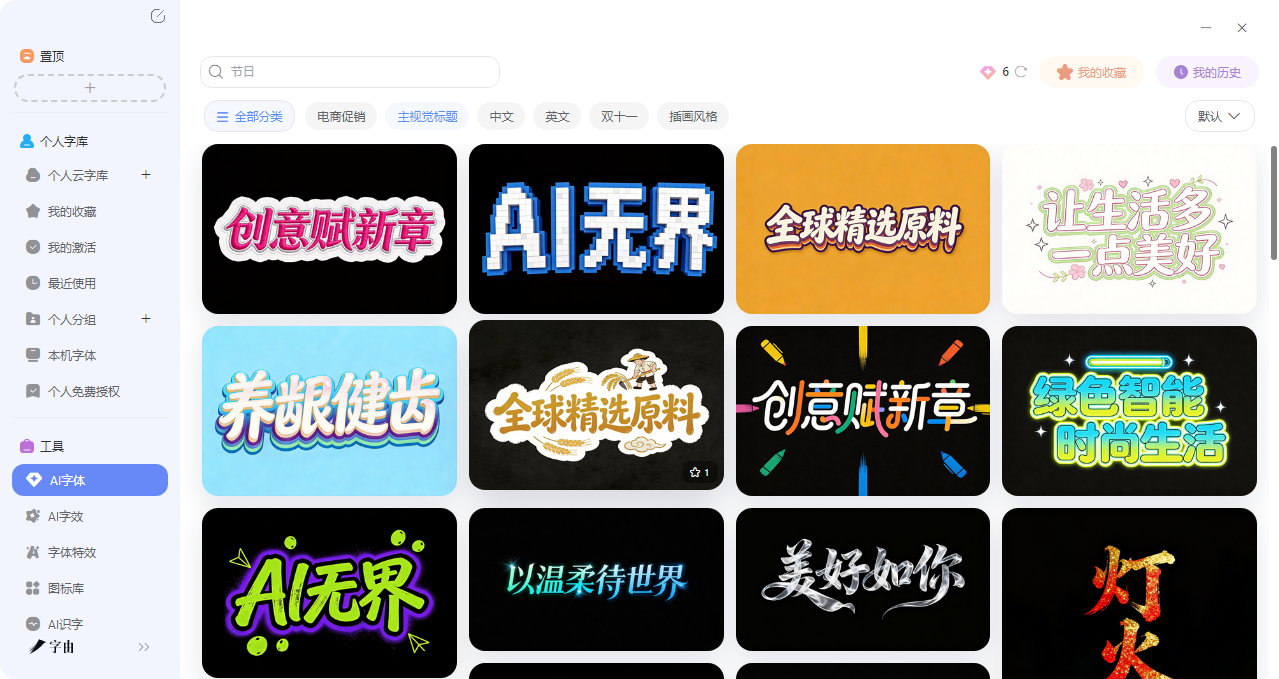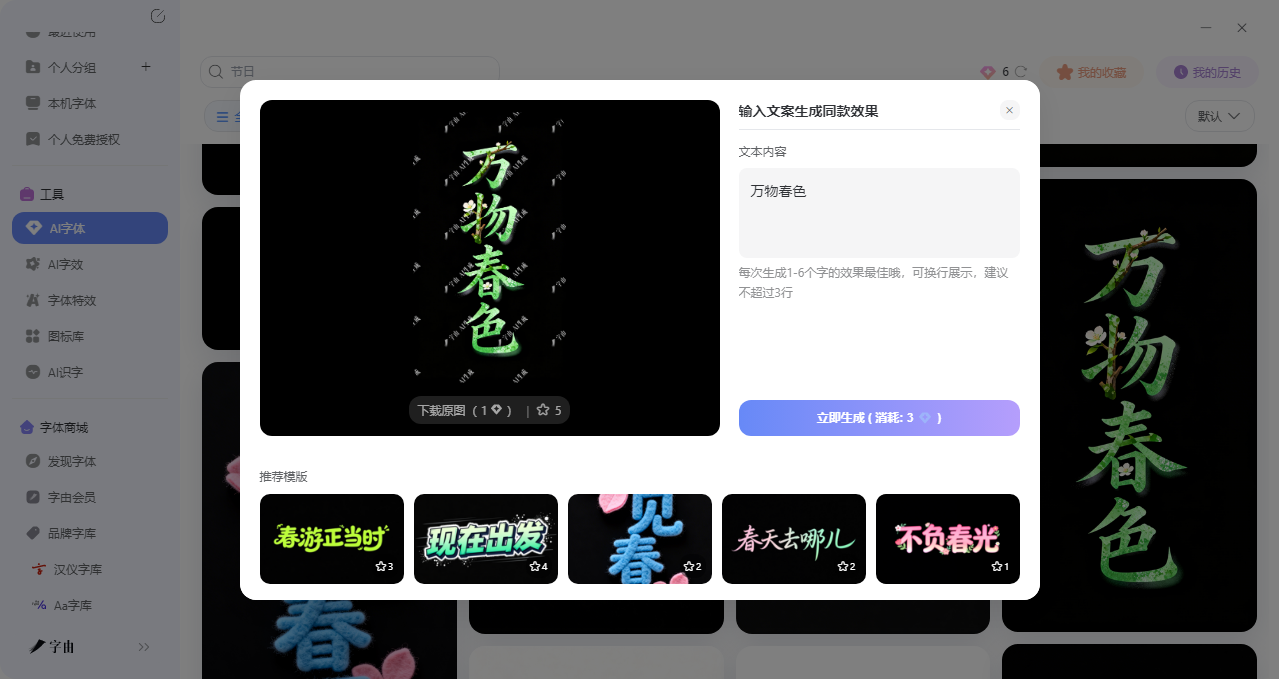
从标题到字幕,视频封面字体用对这个工具就够了
如果你是专门做视频剪辑的肯定都有过这种经历:花了好几天剪辑和拍摄素材,结果上传到视频平台以后播放量却很一般,这样辛苦的付出和平平无奇的收获难免会给自己打击,但是你有没有想过不是你的问题,而是你的封面出了问题?因为封面没有抓住人,观众很难点进来一探究竟。毕竟视频封面就像菜肴的卖相,最起码想让人看了有食欲才能动筷子,字体的选择直接决定了观众愿不愿意点进来。标题要大要醒目,字幕要清晰易读,标签要有风格——同一个封面里,不同位置的文字其实需要不同的字体。有没有一个工具能把这些需求都搞定?字由可以。那么今天这篇就专门讲讲怎么用字由来搞定视频封面字体的所有需求!
1、视频封面用特效AI 字体或更吸引人
视频封面字体的主标题字体是整个封面的视觉中心,这一个一定要足够吸引人、足够抓人眼球。那么字由的AI 字体功能就能够帮你解决如何生成AI 艺术字这个问题。
接下来我将详细介绍怎么用AI 字体做主标题:
第一步:打开AI 字体界面。打开字由客户端,左侧导航栏找到【工具】→【AI字体】,或者从首页【字体工具】→【AI工具】进去。
第二步:选一个适合的视频封面字体。AI字体模板按场景分好了类:电商促销、Banner设计、视频封面、国潮风、科技感等。想做主标题,可以直接点“视频封面”分类,或者按视频类型搜关键词,比如:
- 美食类:搜“诱人”“食欲”“温暖”
- 美妆类:搜“精致”“高级”“优雅”
- 科技类:搜“未来感”“硬核”“极简”
- 旅行类:搜“自由”“远方”“治愈”
每个字体模板都有预览图,可以选一个和自己视频风格相贴近的。
第三步:输入主标题文案。点“做同款”进入编辑页,输入你的视频封面字体文案。注意:最好和模板字数保持一致,这样生成效果最自然。比如模板是四个字,你就填四个字;模板是两个字,你就填两个字。
2、副标题/其他信息字体:用字体库选免费商用字体
除了主标题,视频封面上通常还有辅助信息,比如“全网首测”“干货满满”“建议收藏”这种小标签,或者一些解释性的副标题。这些文字不需要太花哨,但要清晰易读、风格统一。字由的字体库里有超过 10500 款字体,其中3584 款是免费可商用的。但是也不用怕字体太多太乱,只要合理运用筛选功能,很快就能找到合适的。
第一步:按风格选字体。打开字由客户端,左侧有“免费字体”选项,点进去以后可以在右上角的筛选项来选择你想要的字体风格:
- 现代:适合科技、数码类视频
- 手写风:适合生活、Vlog、治愈类
- 可爱:适合母婴、萌宠、美食类
- 力量/豪放:适合运动、硬核测评类
- 端庄优雅:适合美妆、时尚类
第二步:按字重调粗细
同一个字体可能有不同字重:
- 纤细/细:适合做小字点缀,比如标签、副标题
- 正常:最常用,适合正文信息
- 粗/超粗:视觉冲击力强,适合次级标题
第三步:预览试字。点进感兴趣的字体,可以在预览框里输入你的文案(比如“全网首发”),实时看效果。确定视频封面字体合适了再免费下载应用。
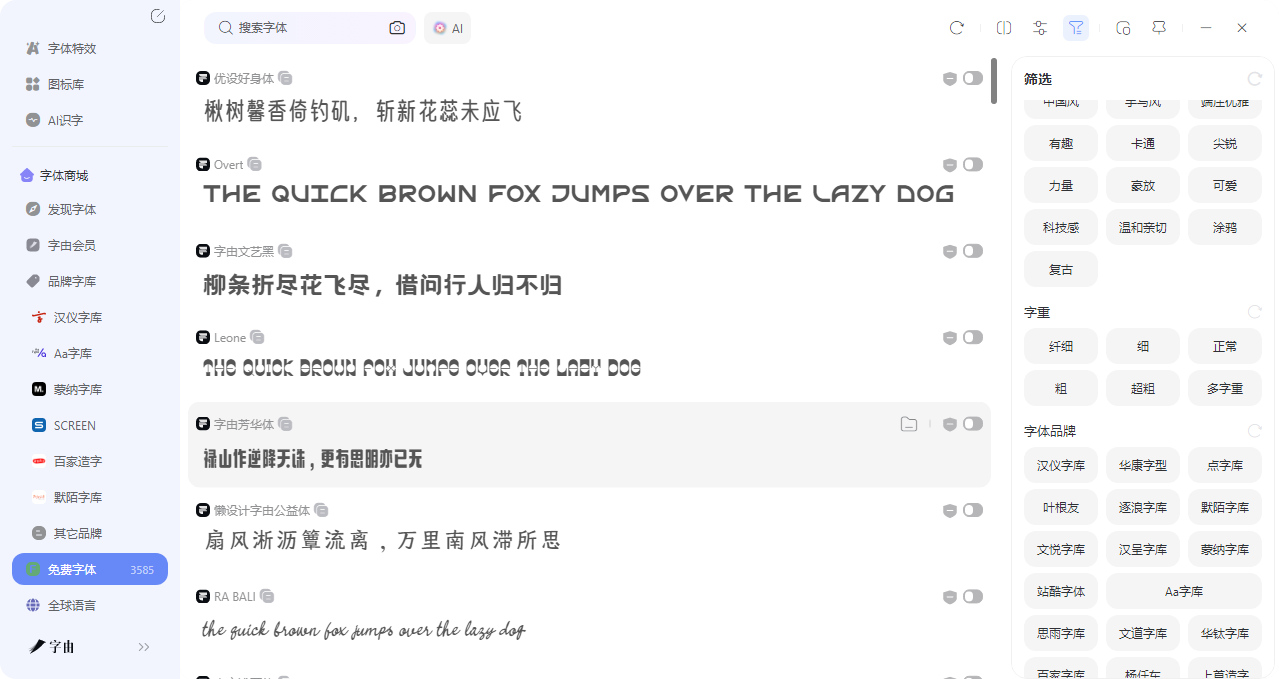
3、字体推荐
我这里还会为大家准备一些适合的视频封面字体:
- 优设标题黑:方正有力,适合科技、数码类视频标题
- 字由文艺黑:既有黑体稳重又带手写感,适合生活、Vlog
- 字由芳华体:温柔手写风,适合治愈系、情感类视频
- 点字爨宝子:圆润可爱,适合母婴、萌宠、美食类
- 江西拙楷:国风感强,适合传统文化类视频
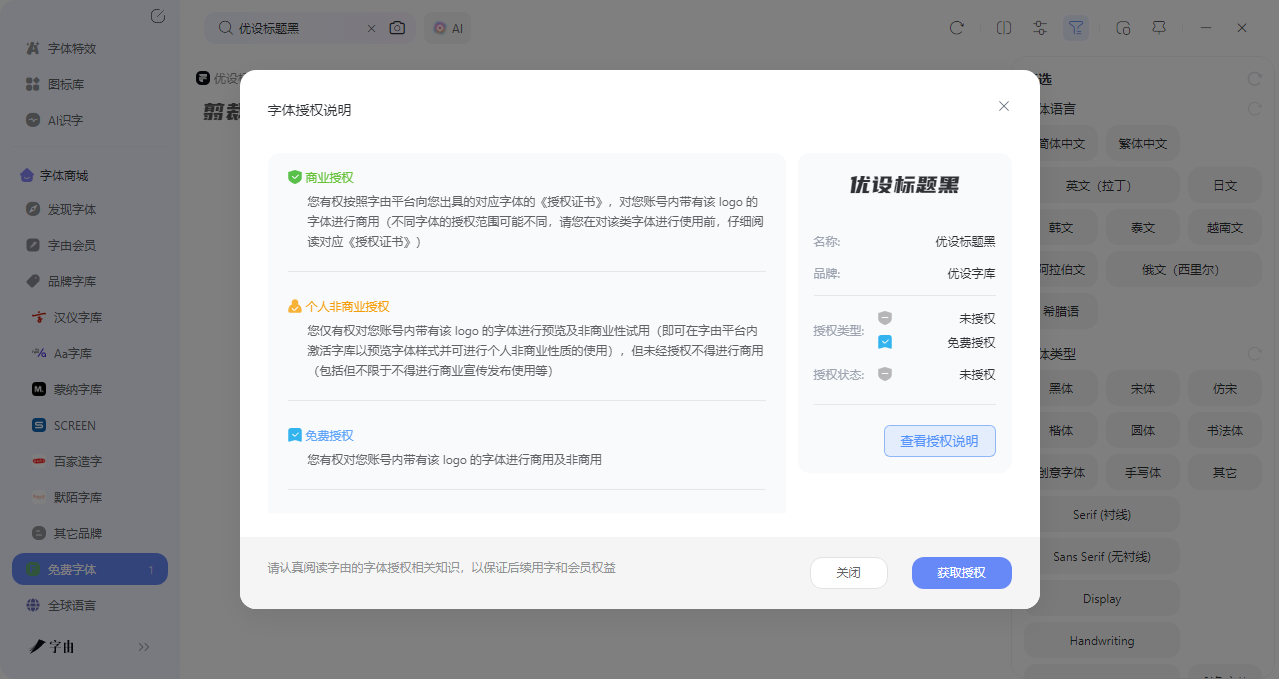
话说回来,一个视频的爆火和封面有很大的关系,标题足够吸引人、设计足够突出重点都是十分关键的,而字体也是承载这种信息的载体,正是封面里最能直接传递情绪的元素。好的字体能让观众为你的视频驻足停留,说到底是在帮你的内容争取那一秒的机会。字由一个工具,从AI 字体到免费下载字体,再到一键应用字体到设计软件,可以解决一切你头疼的问题。如果你也在为视频封面发愁,不妨打开字由试试。